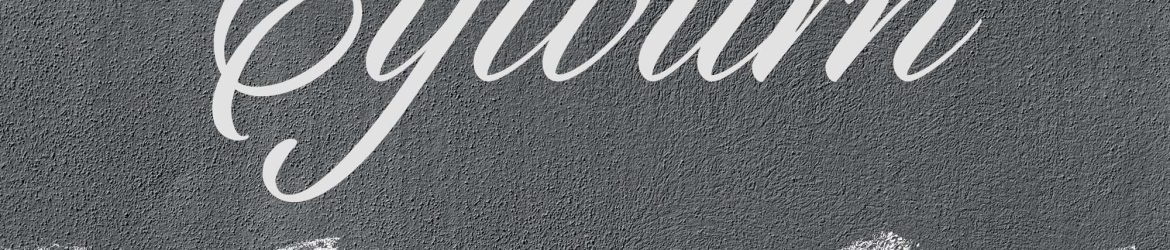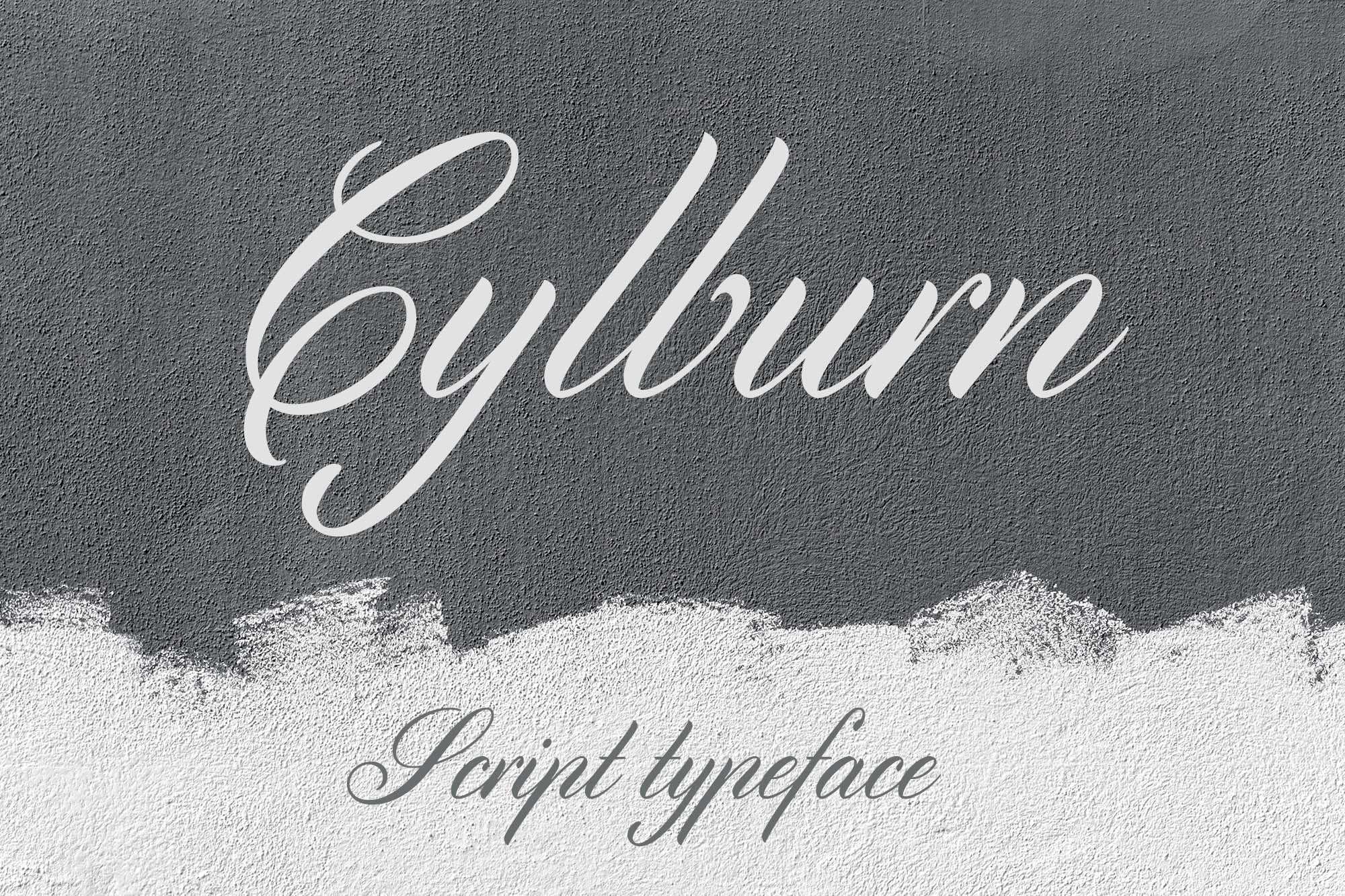
Cylburn Free Script Font – Download Grátis
Cylburn Free Script Font
Cylburn Regular é uma fonte de escrita gráfica que oferece uma sensação natural e envolvente, perfeita para projetos gráficos variados. Essa fonte semi-conectada foi criada pelo designer Dai Foldes e traz um toque de cunho cíliar, com sua escrita feita com uma espada pontiaguda e tensão contida, o que a faz se destacar em comparação com outras fontes de escrita cíliar de formato circular. Suportando tanto letras maiúsculas quanto minúsculas, números e caracteres especiais, essa fonte é perfeita para adicionar um toque elegante a cartões de convite, painéis, cabeçalhos e muito mais. Além de estar disponível no formato OTF, também está disponível no formato TTF. Perfect para projetos que precisam de uma escrita gráfica única e envolvente.